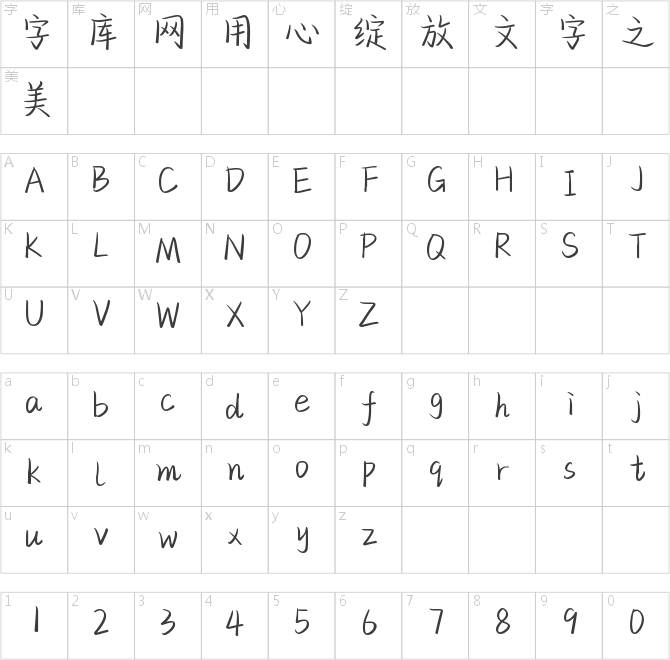
字體名稱: 你的眼底滿是溫
你的眼底滿是溫柔
你的眼底滿是溫柔介紹
你的眼底滿是溫柔字體字庫(kù)是一款讓人賞心悅目、百看不厭的中文字體,適合各類廣告和產(chǎn)品包裝設(shè)計(jì)應(yīng)用,字體大小3.35MB,格式為ttf字體,上傳用戶是文道字庫(kù),作者/版權(quán)方為文道字庫(kù)